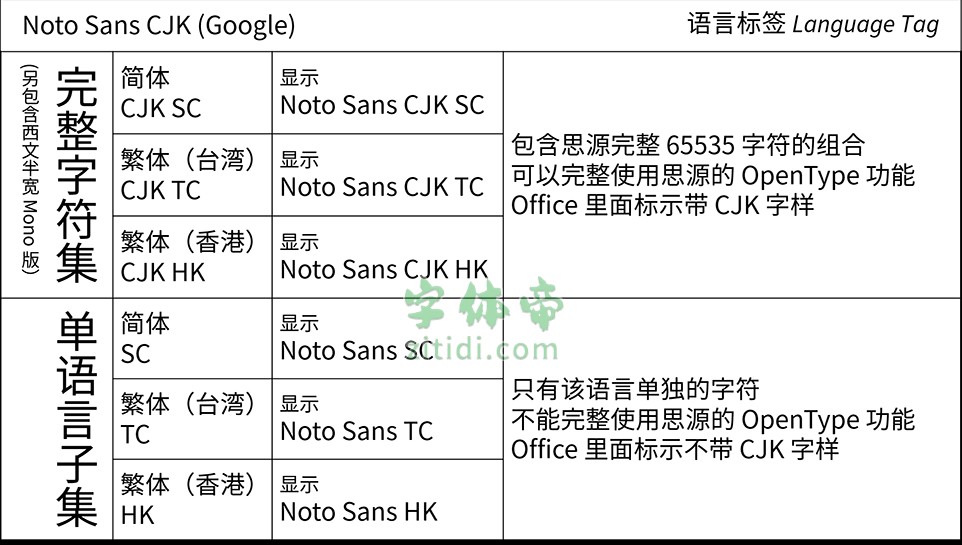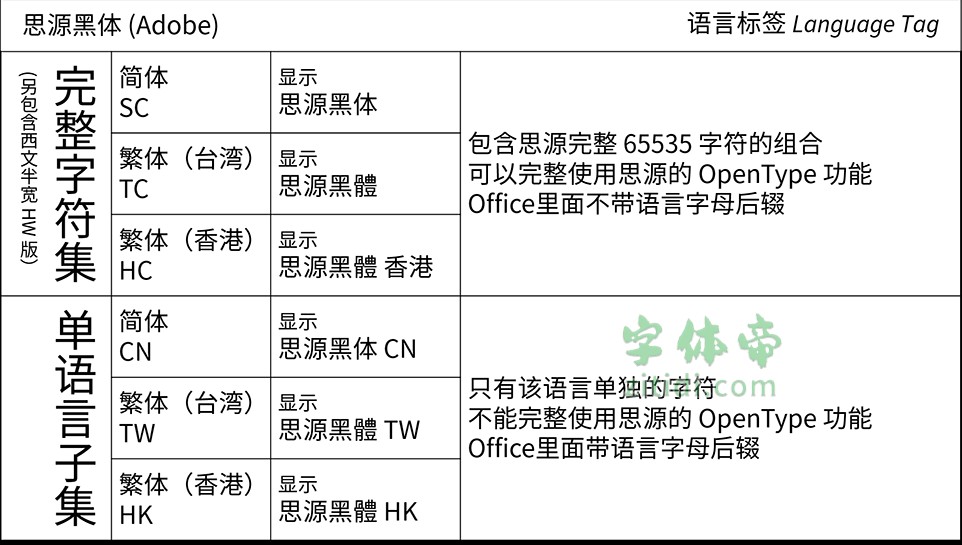
思源黑体 CN字体信息
思源黑体 CN
字体名称: 思源黑体 CN
字体风格: 黑体
思源黑体 CN字体预览
说起思源黑体,也不用太多的介绍了,估计做设计的朋友们应该都会知道这款字体。这是Adobe与Google历时三年在2014年7月宣布推出的一款开源字体,这种字体有七种字体粗细(ExtraLight、Light、Normal、Regular、Medium、Bold 和 Heavy),完全支持繁体中文、简体中文、日文和韩文,这些全部都包含在一种字体中。
思源黑体有两个版本,一个是Adobe发布的版本,一个是谷歌发布的版本。这两个版本有什么不同呢?
1、字体名称不同
这两个版本的区别是字体的名称不同。Adobe版本在PS中显示的字体名称是“思源黑体”,而谷歌版本在PS中显示的字体名称是“Noto Sans CJK”
2、字重的名称不同
Adobe版本的字重名称是:ExtraLight、Light、Normal、Regular、Medium、Bold 、Heavy。
Google版本的字重名称是:Thin、Light、DemiLight、Regular、Medium、Bold、Black
字体文件里的CN、HK、TC、SC、TW等是什么意思?
思源黑体 CN”是一款书写很新颖的字体,字体大方,适合各种设计作品使用!欢迎下载!